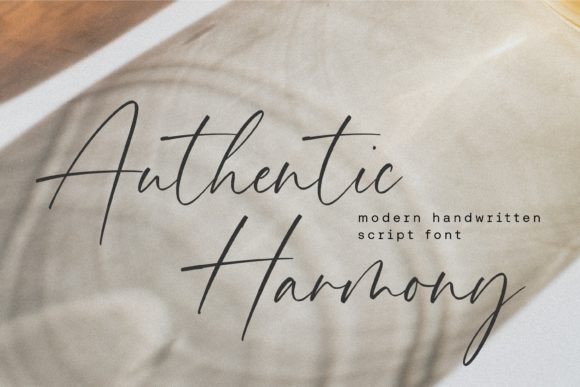
Authentic Harmony
POD(์ฃผ๋ฌธํ˜• ์ธ์‡„) ์ œํ’ˆ, ๊ฒฐํ˜ผ์‹ ์ดˆ๋Œ€์žฅ ๋˜๋Š” ์†Œ์…œ ๋ฏธ๋””์–ด ๊ทธ๋ž˜ํ”ฝ์„ ๋งŒ๋“ค ๋•Œ Authentic Harmony๋Š” ์ด์ƒ์ ์ธ ์„ ํƒ์ž…๋‹ˆ๋‹ค.